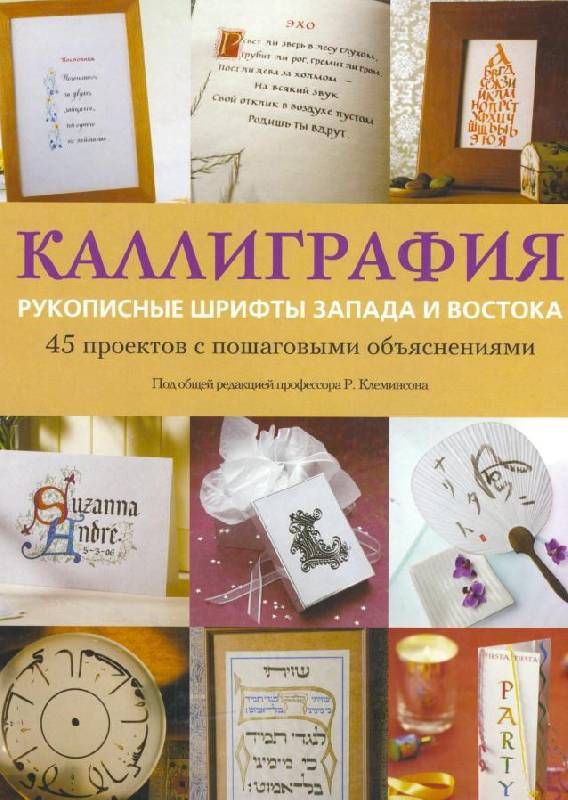
Каллиграфия. Рукописные шрифты Запада и Востока (Роберт Клеминсон)
Познакомьтесь с древним искусством каллиграфии!
Каллиграфия - это не только наука, которую интересно изучать самому, но и способ сделать оригинальный подарок своим близким, друзьям и знакомым.
В книге вы найдете целый ряд упражнений, которые научат вас тому, как сделать такой подарок, — поздравительную открытку, красиво написанное стихотворение, табличку с именем, расписной абажур для лампы, японский веер или оригинальную шкатулку.
Эта книга написана авторским коллективом известных и компетентных современных каллиграфов и художников.